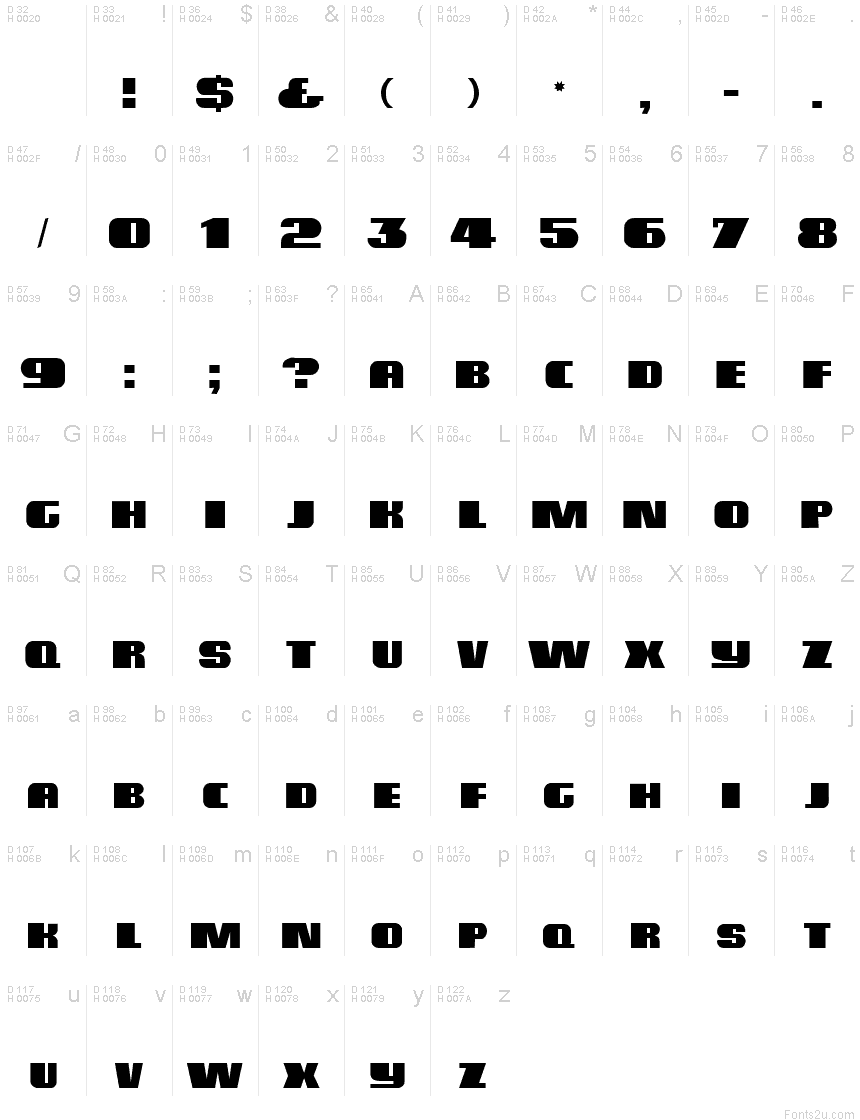
Miele to darmowy geometryczny krój bezszeryfowy o prostych, blokowych kształtach i ostrych wycięciach, które nadają projektowi mocny, industrialny rytm. Równomierna grubość kresek i kwadratowe formy sprawiają, że tekstura pisma jest prosta i graficzna, ale nie sprawia wrażenia nudnej.
Miele świetnie sprawdza się w logotypach, tytułach na plakatach, opakowaniach, oznakowaniach i krótkich banerach internetowych, gdzie rygorystyczny, strukturalny charakter pisma bezszeryfowego pomaga uzyskać bezpośredni przekaz. Pasuje również do akcentów redakcyjnych i znaków marek, ponieważ znaki zachowują spójny kształt, co nadaje krótkim liniom tekstu przejrzysty i uporządkowany charakter.